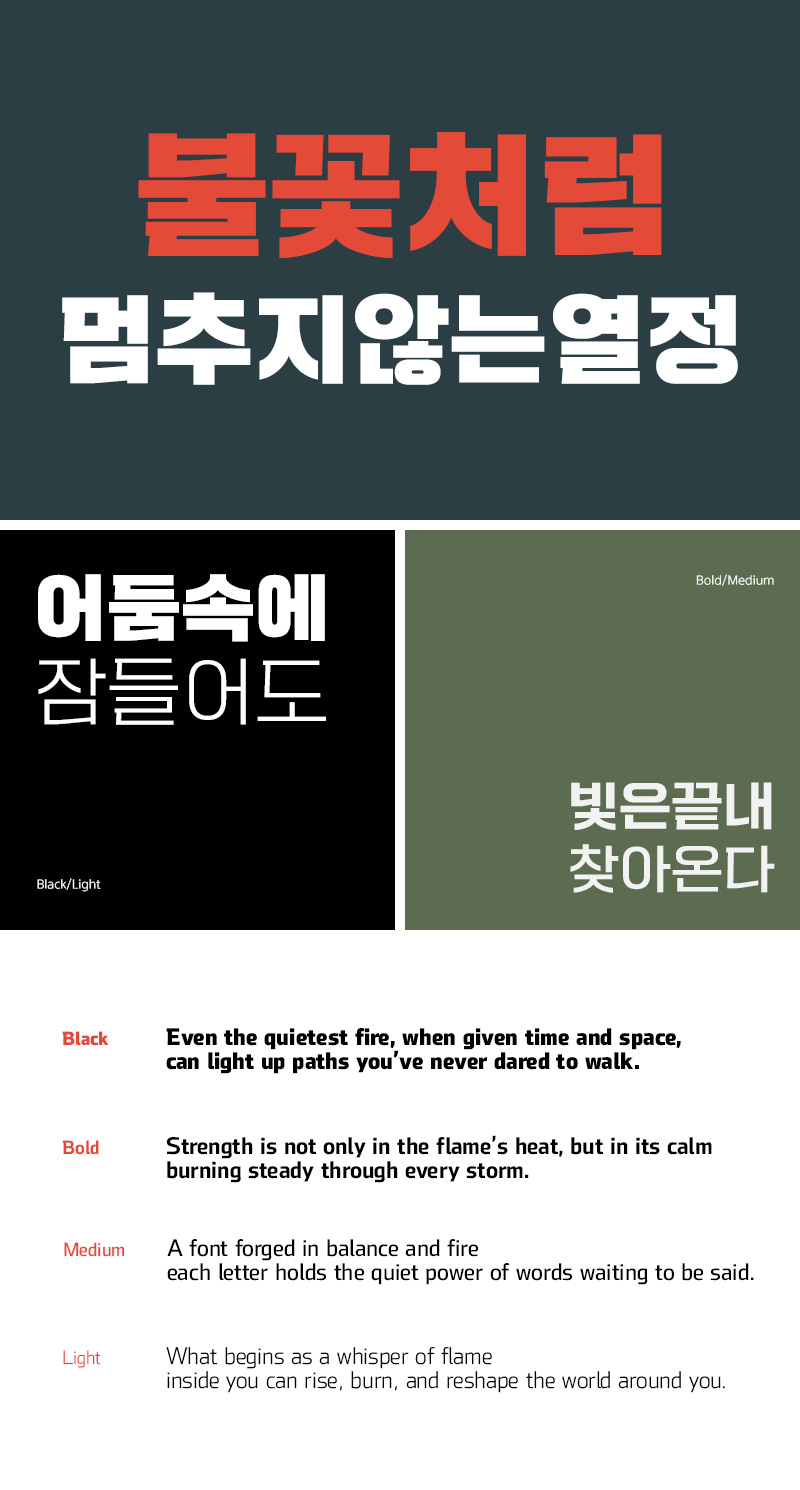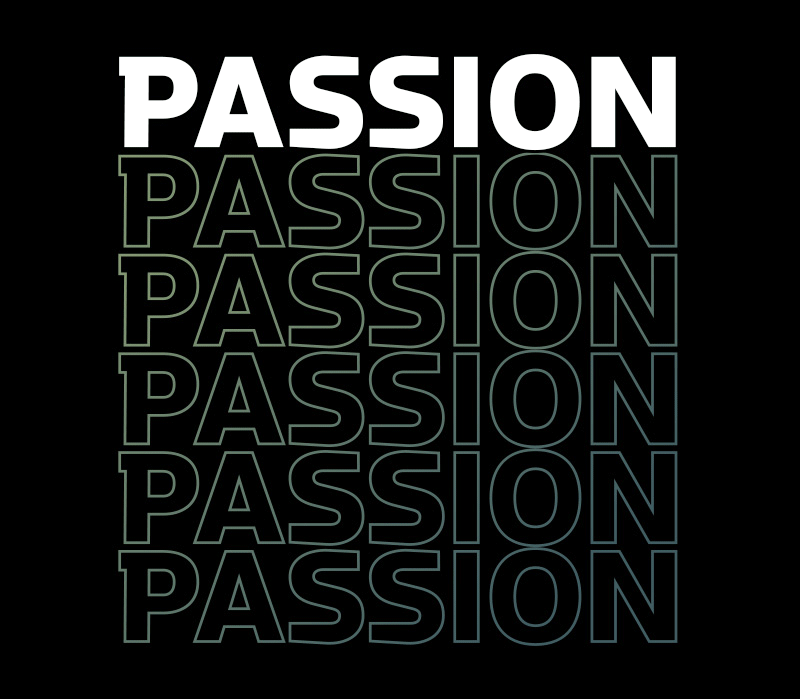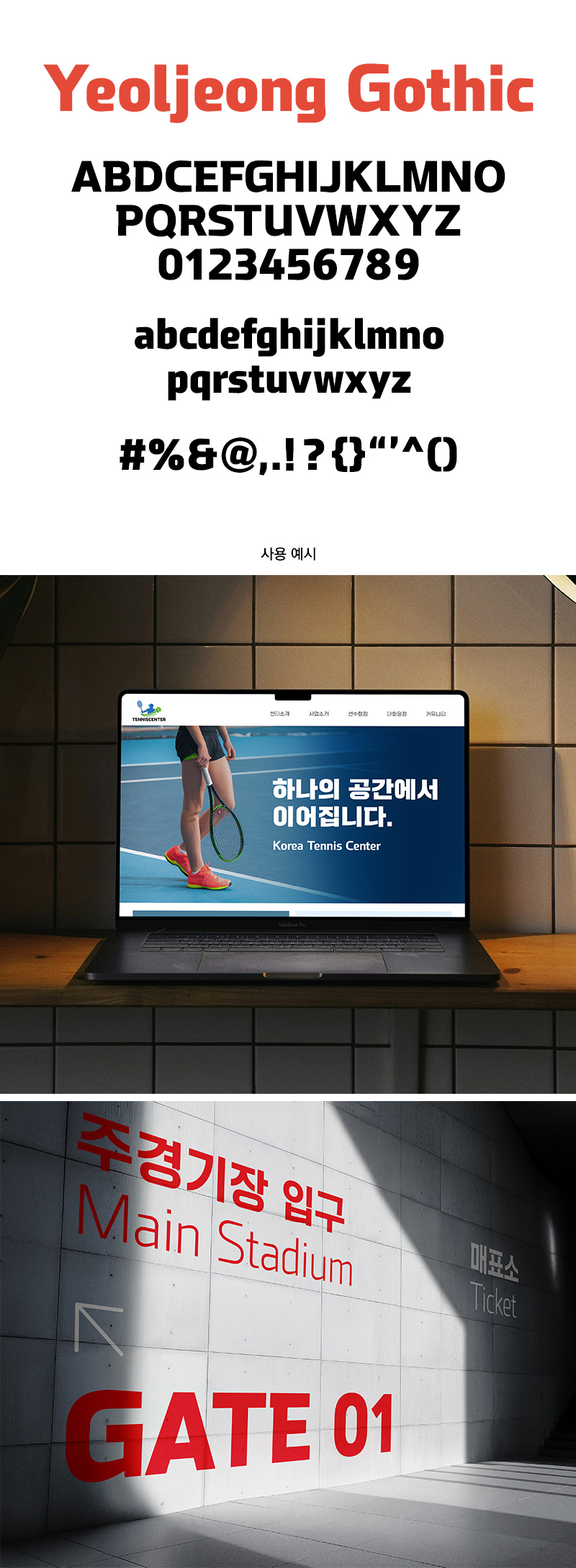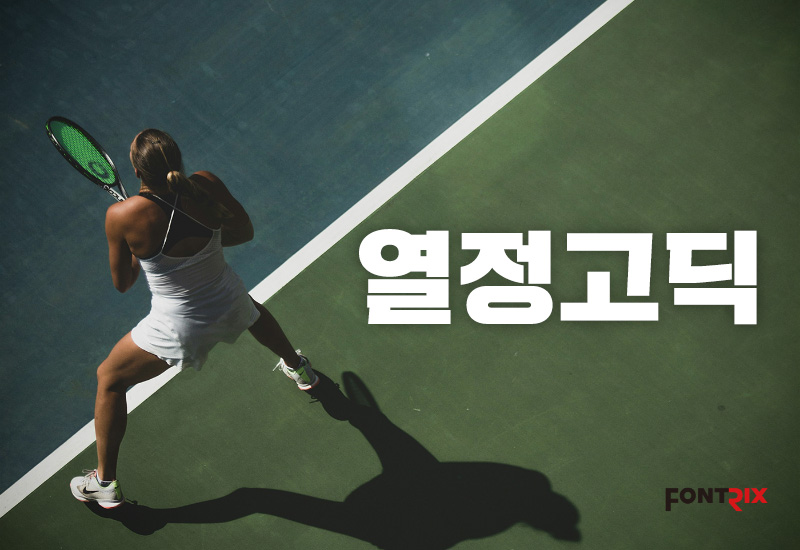
RixYeoljeongGothic
4 Style - Black, Bold, Medium, LightRix열정고딕은 정방형의 꽉 찬 골격으로 묵직하지만 획이 속도감 있는 서체입니다.
4가지 웨이트로 풍부하게 구성되어 있어 사용성을 높였으며,
가장 두꺼운 두께인 Black은 묵직하고 단단한 제목용으로 적합합니다.
| FontFamily | Rix열정고딕 / RixYeoljeongGothic |
| Design | Choi Beop-Ho, Park Min-woo |
| Direction | Park Yong-rak |
| Glyphs | 2,350 + 430 KR Characters / 94 Latin Characters / 986 Symbols |